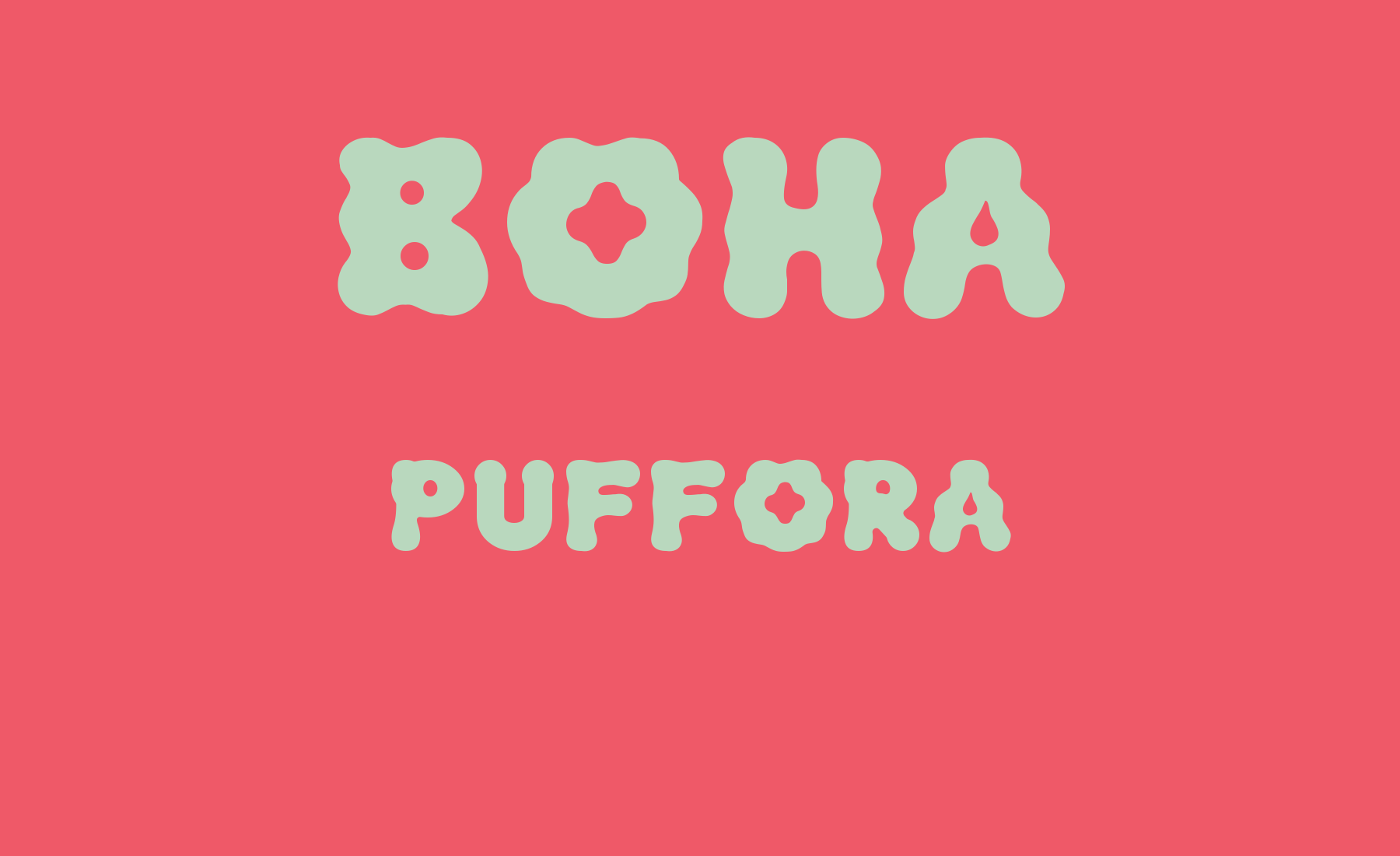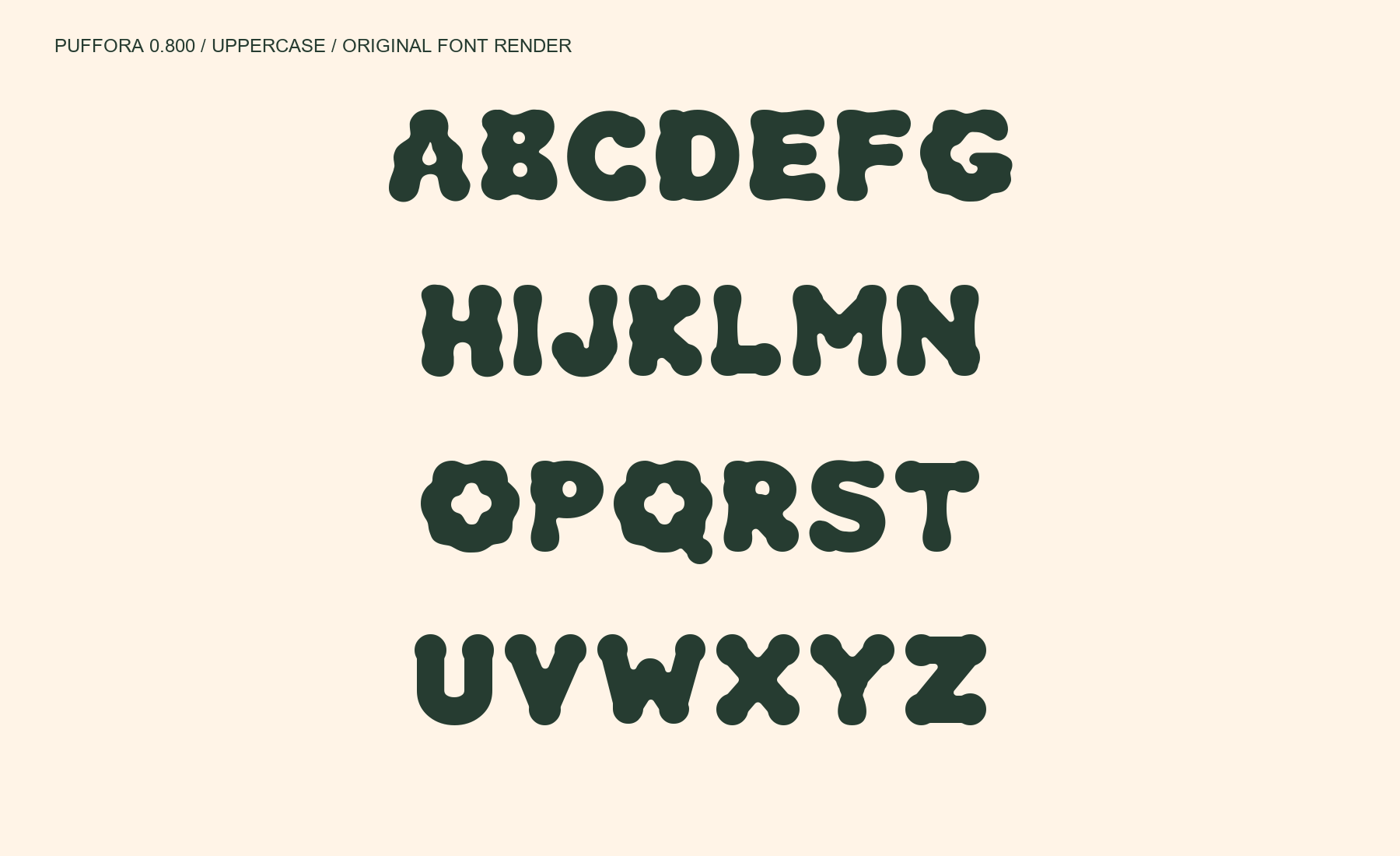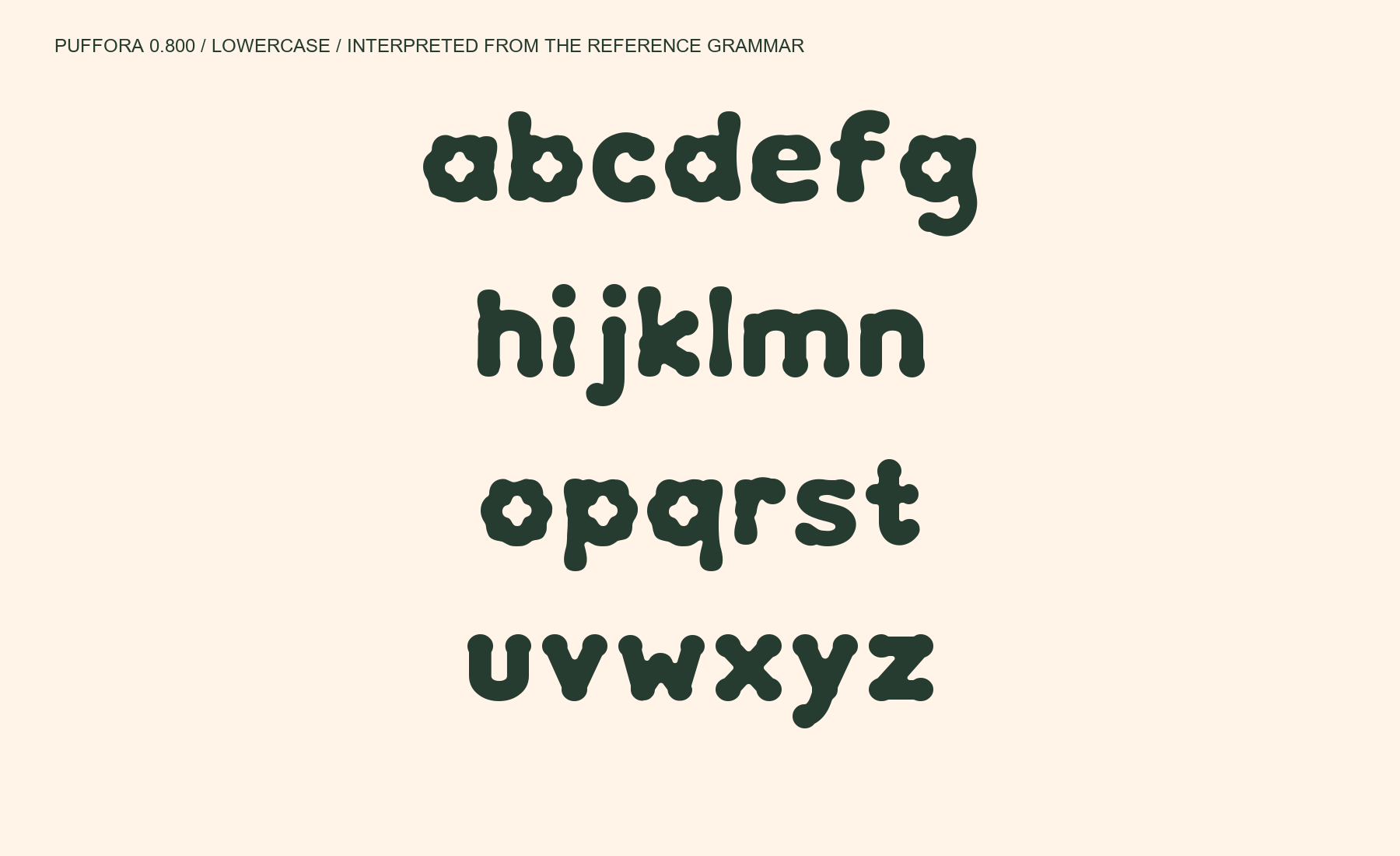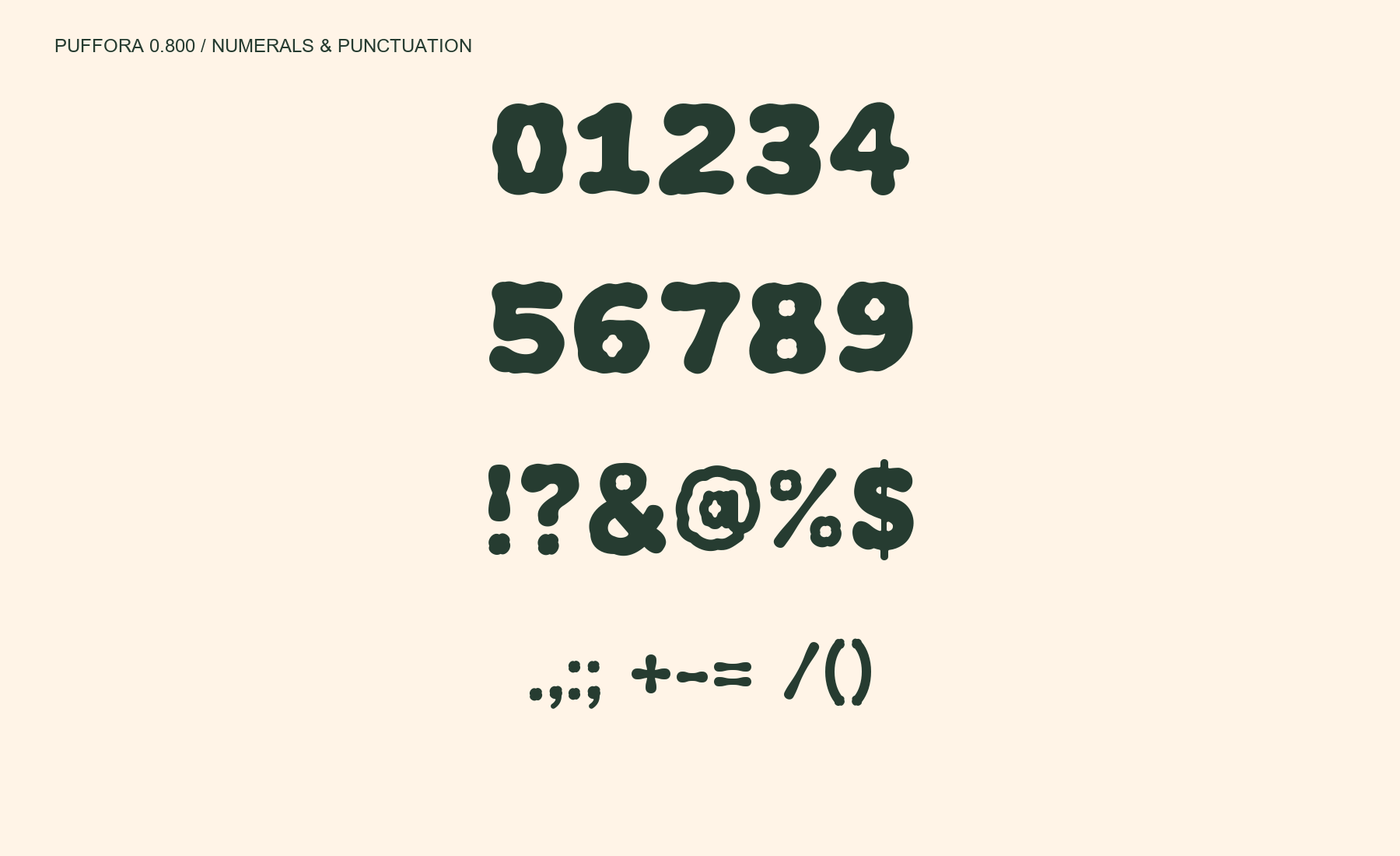
Latin only. No Hangul.
Puffora는 부풀어 오른 둥근 끝과 잘록한 연결부, 꽃잎처럼 열린 속공간을 가진 초굵은 버블 디스플레이 서체입니다. B의 작은 원형 속공간, O의 네 잎 형태, H의 둥근 기둥과 A의 물방울 속공간이 개성을 만듭니다. 숫자와 기호에도 풍성한 볼륨과 유연한 굴곡을 적용했습니다. Regular 0.800 · 라틴 330자(공백 2자 포함). 영문 대소문자, 숫자, 확장 라틴 악센트와 기호를 지원합니다. 한글은 포함하지 않습니다. TTF와 WOFF2를 하나의 ZIP으로 제공하며 SIL Open Font License 1.1로 무료 배포합니다. 72px 이상 제목·포스터·패키지에 권장합니다. 작은 크기에서는 좁은 속공간과 꽃잎 모양의 디테일이 약해질 수 있습니다. 0.800에서는 숫자 2·3·7과 관련 분수, @·ð·Ħ·¶·ŧ·æ의 연결부와 속공간을 다듬었습니다. 전체 330자의 확대 표본과 파일 구조를 점검했습니다. 모든 문자쌍의 커닝 및 운영체제별 호환성 검수는 완료하지 않았습니다.